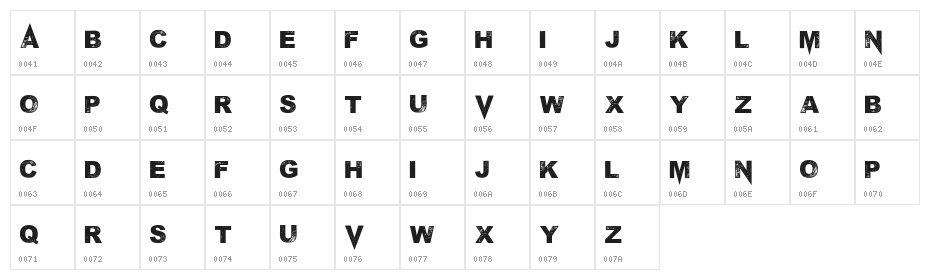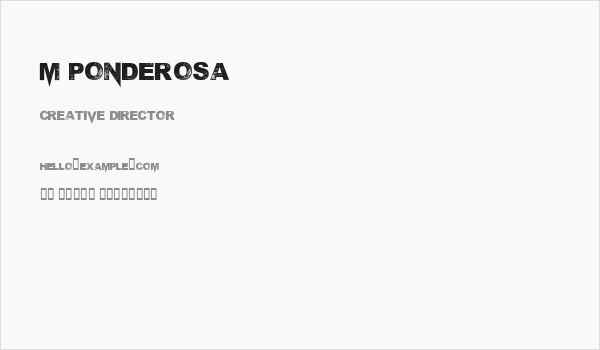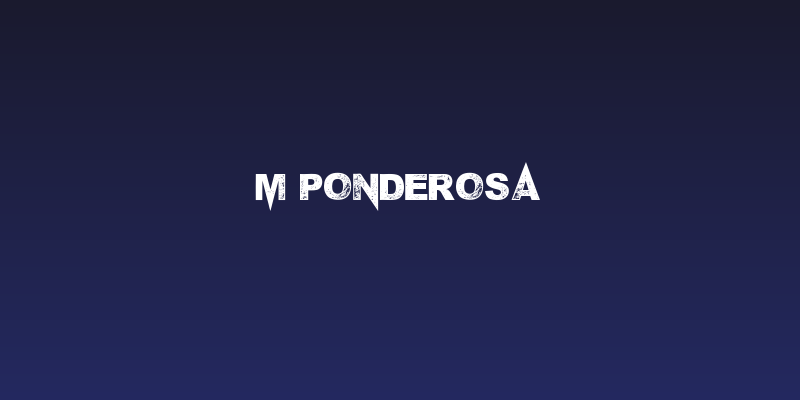
M Ponderosa Font
✎ Distorted Eroded
M-PONDEROSA MAIUSCOLE
M-PONDEROSA MINUSCOLO
M-PONDEROSA ALTRI CARATTERI
| Categorie | Distorted Eroded |
| Stile generale | Vintage, Industrial |
| Progetti proposti | Ideal for vintage posters, industrial-themed branding, or any project needing a bold, eye-catching typeface. |